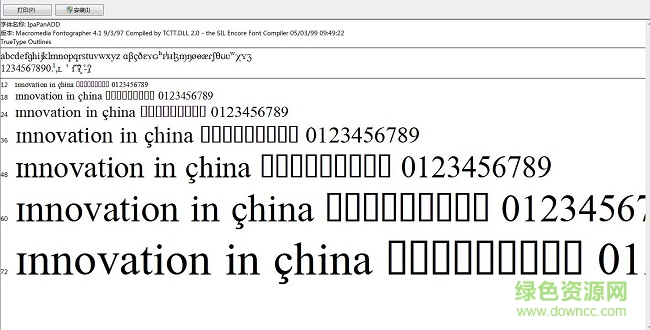
ipanpan.ttf怎么用?音標(biāo)字體ipanpan.ttf是一款獨(dú)特的國際音標(biāo)字體,可以顯示多國語言,漢語拼音、阿拉伯字母都支持,對于大家的英語音標(biāo)學(xué)習(xí)很有幫助,需要的朋友快來下載吧!
國際音標(biāo)遵循“一音一符”的嚴(yán)格標(biāo)準(zhǔn),最初用于為西方語言、非洲語言等的標(biāo)音。經(jīng)過多年發(fā)展,在中國語言學(xué)者趙元任等人的努力下,國際音標(biāo)逐漸完善,已可為漢語等東方語言注音。
國際音標(biāo)形式上,以拉丁字母(羅馬字母)的小寫印刷體為主,如:[a、b、c、d、f、g、h、i、j、k、p]等。